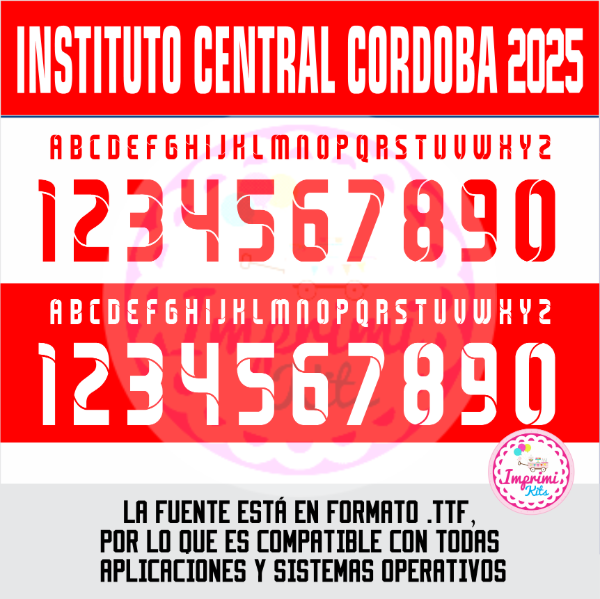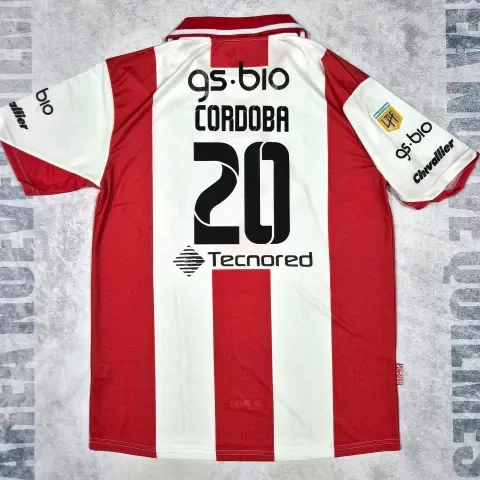
Tipografia Instituto Central Córdoba 2025 Camiseta Ttf Otf Numeros Dorsal
Tipografía Números Fuente
Realizá todo tipo de creaciones con la tipografía utilizada actualmente en el club